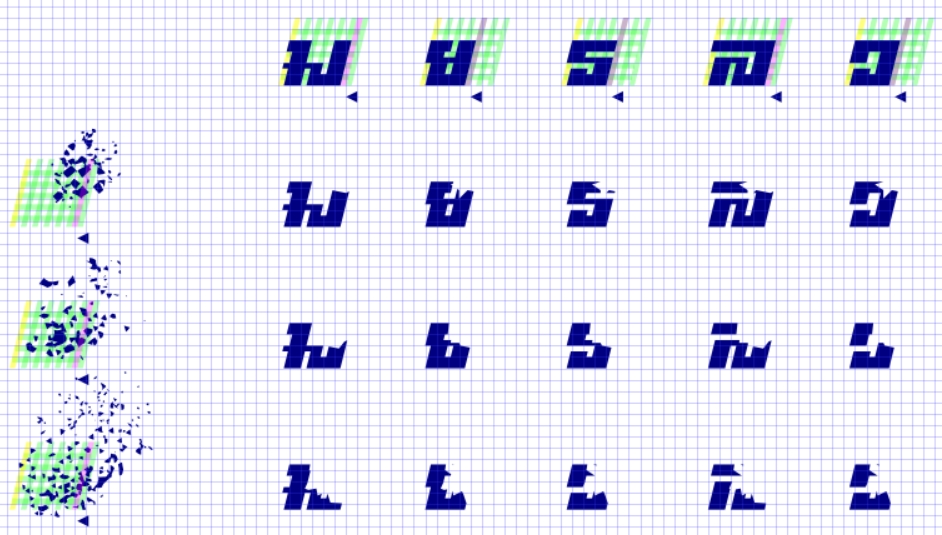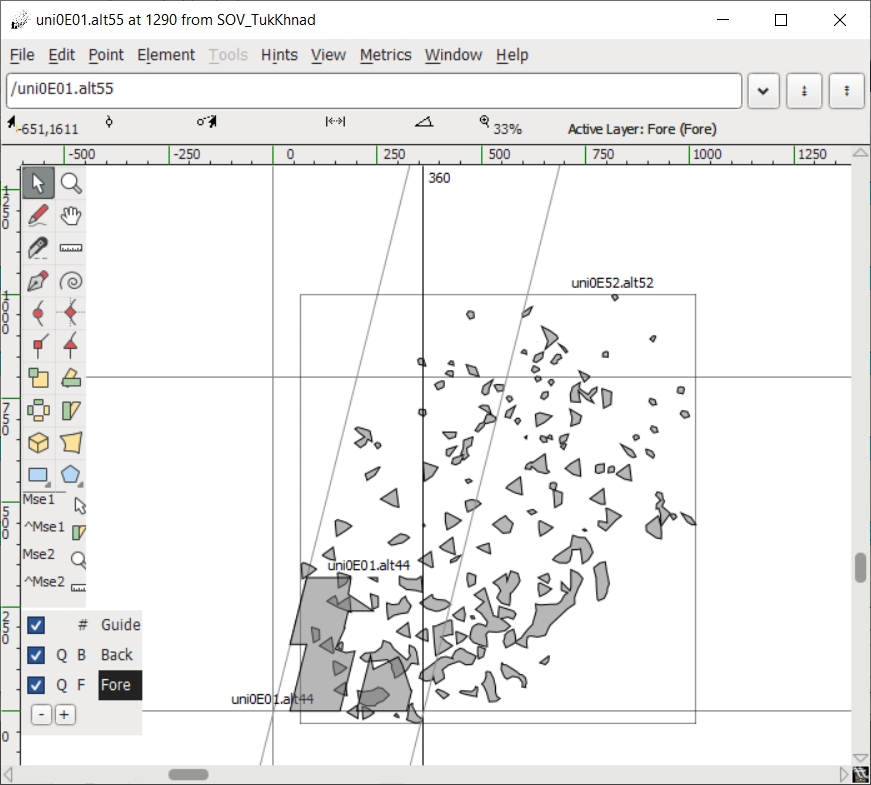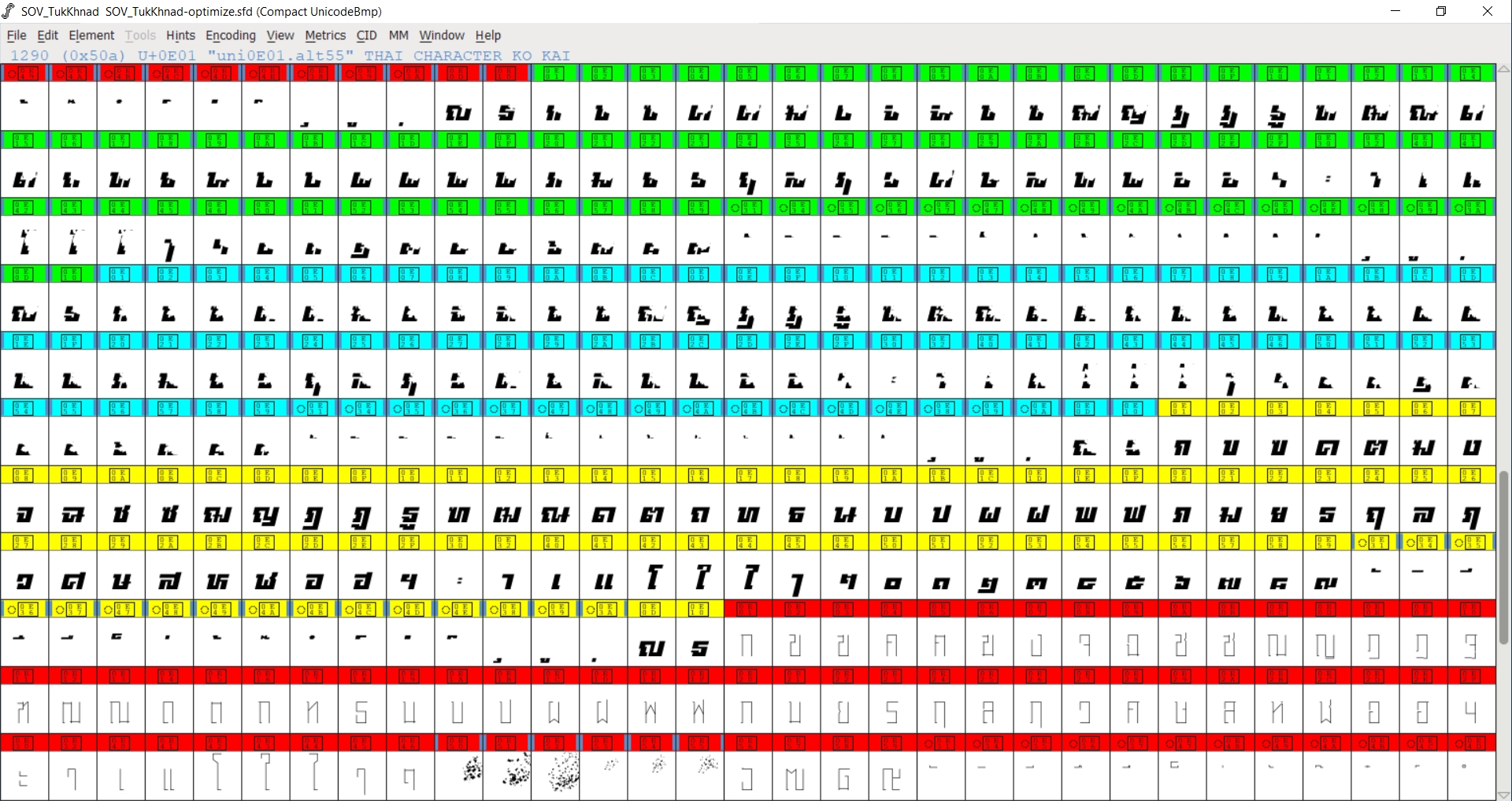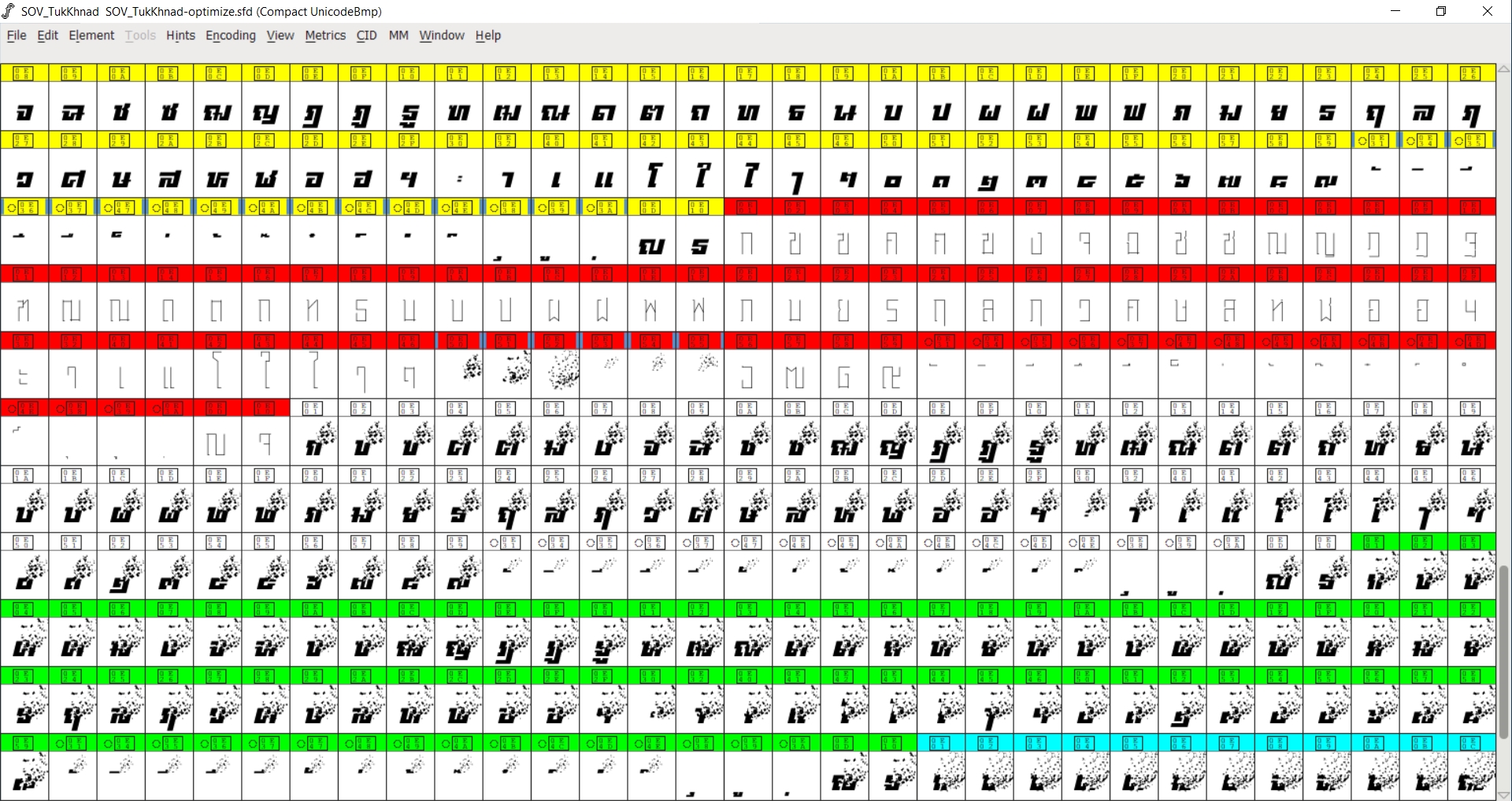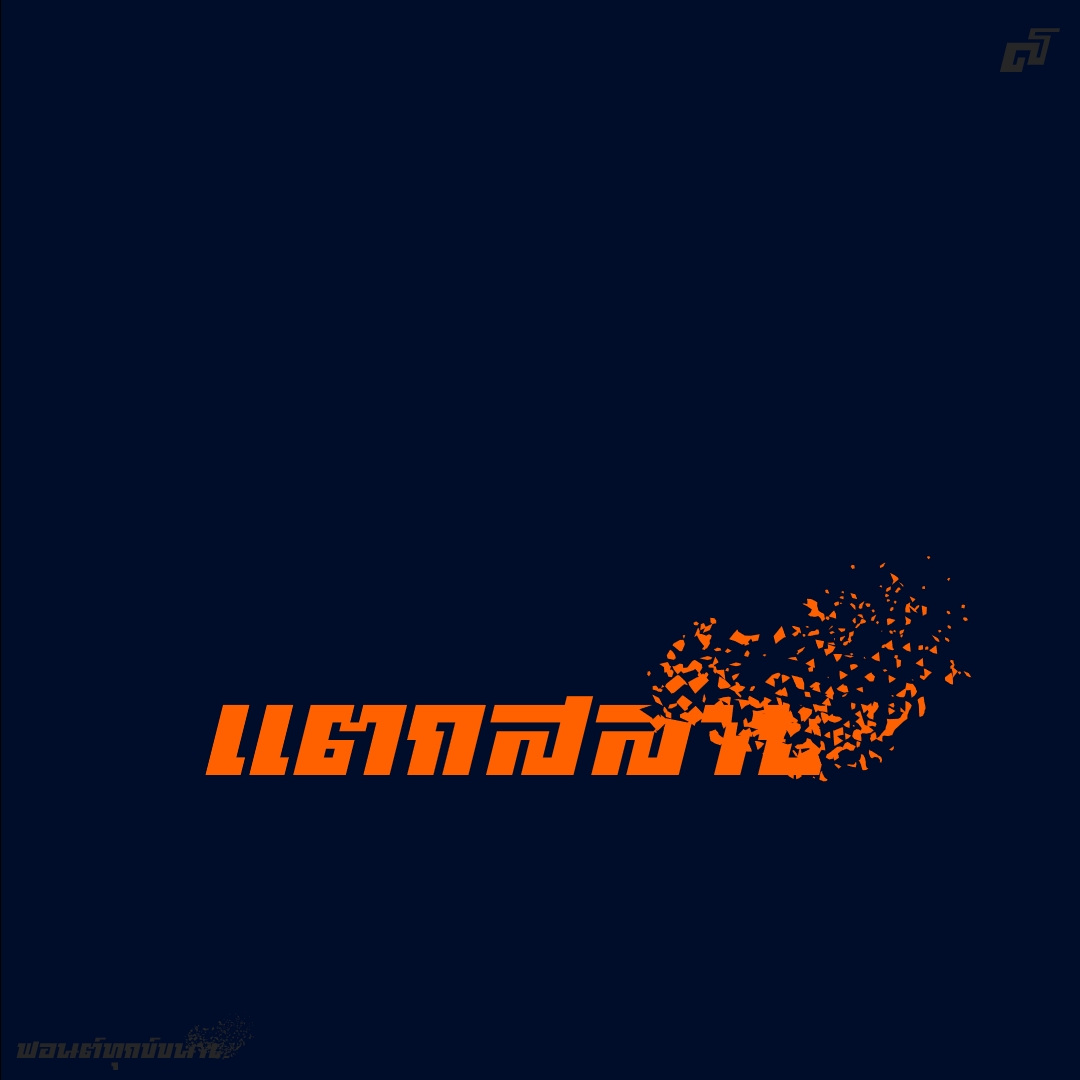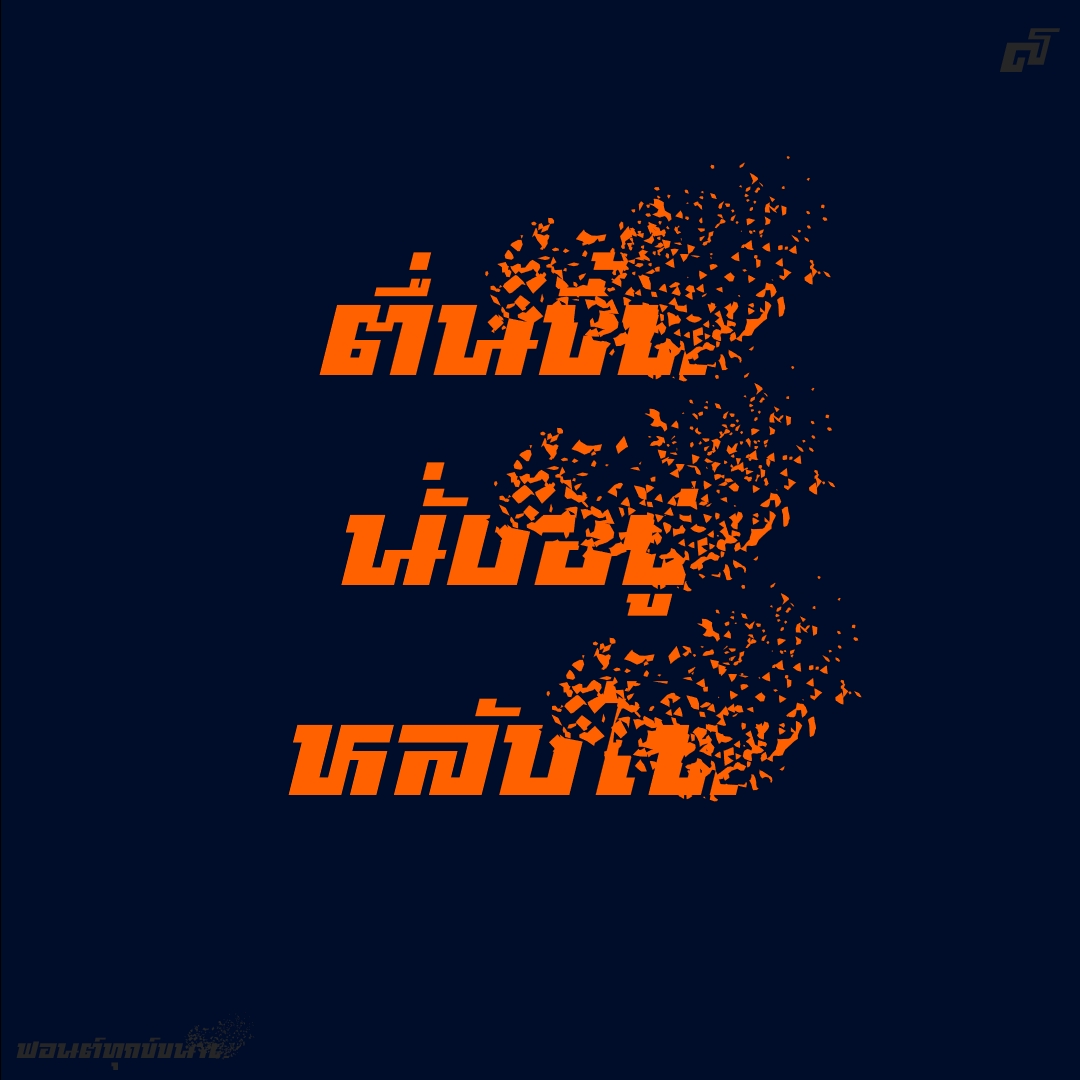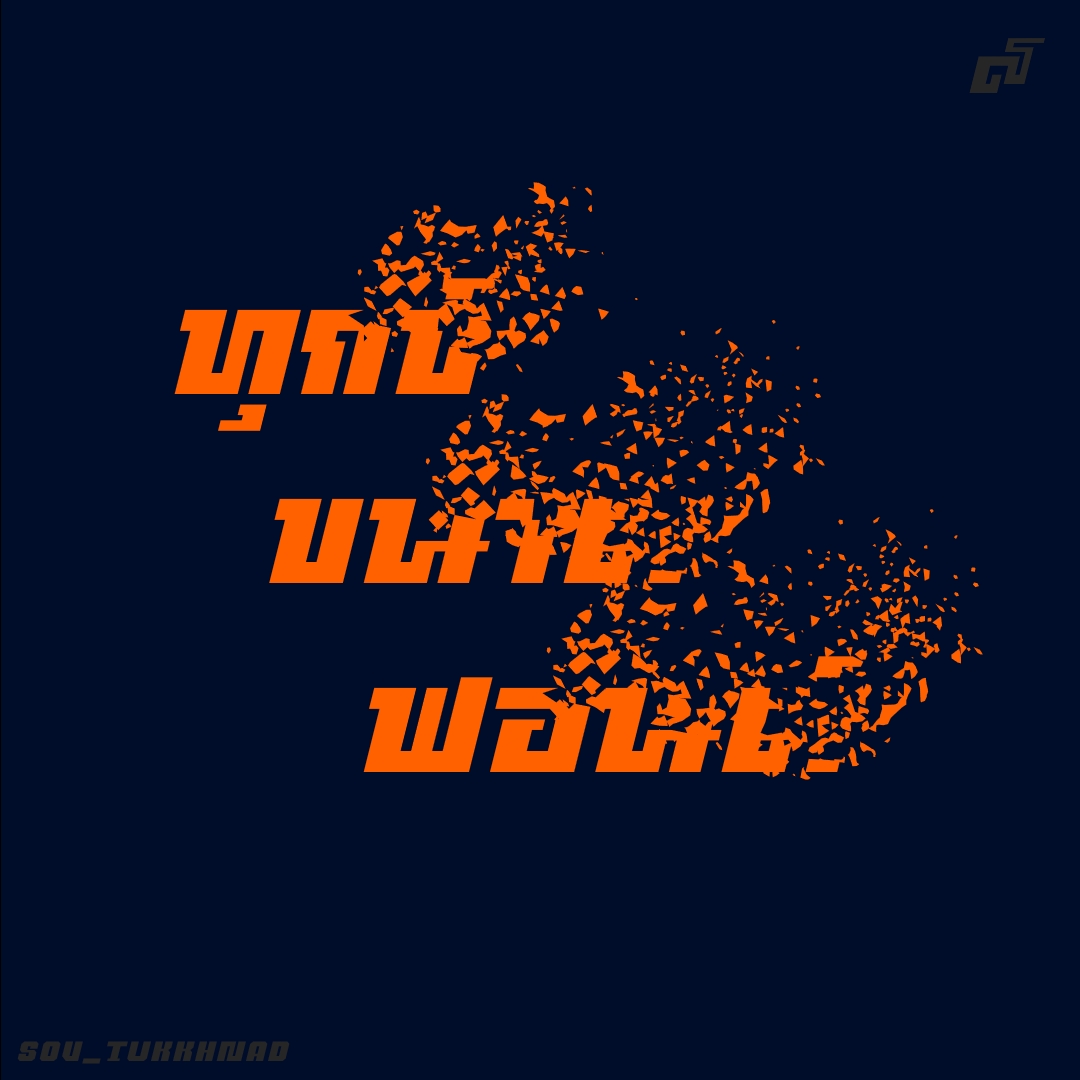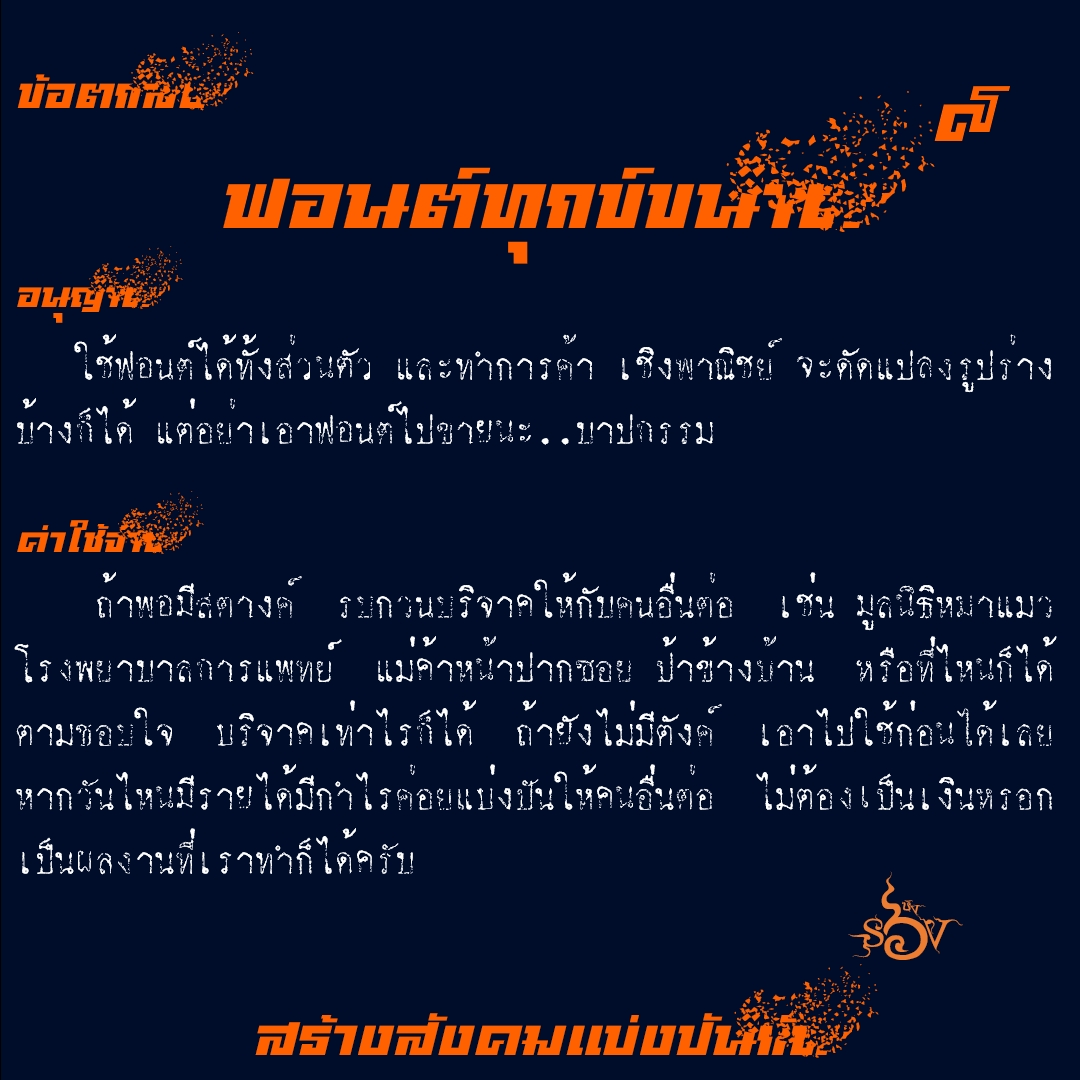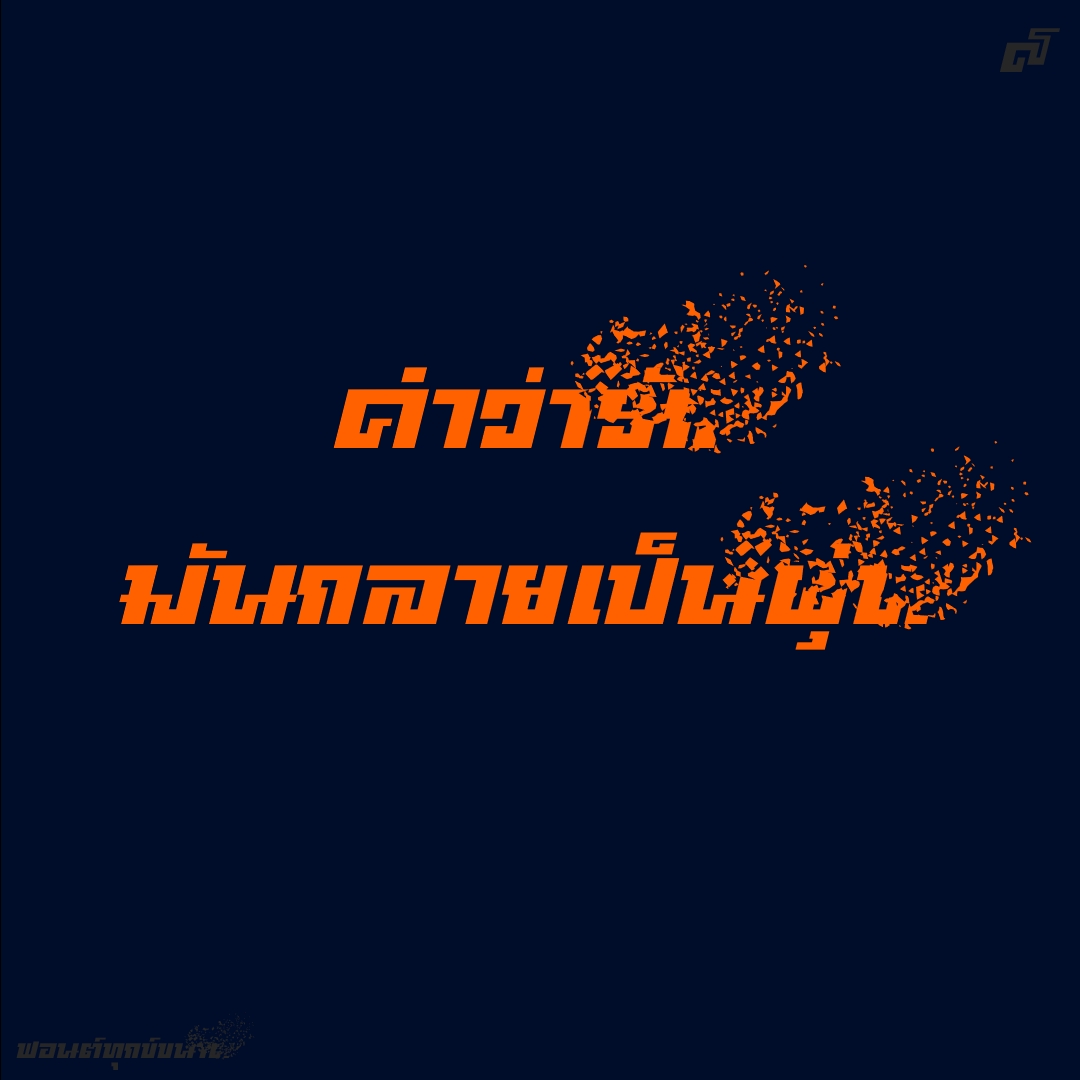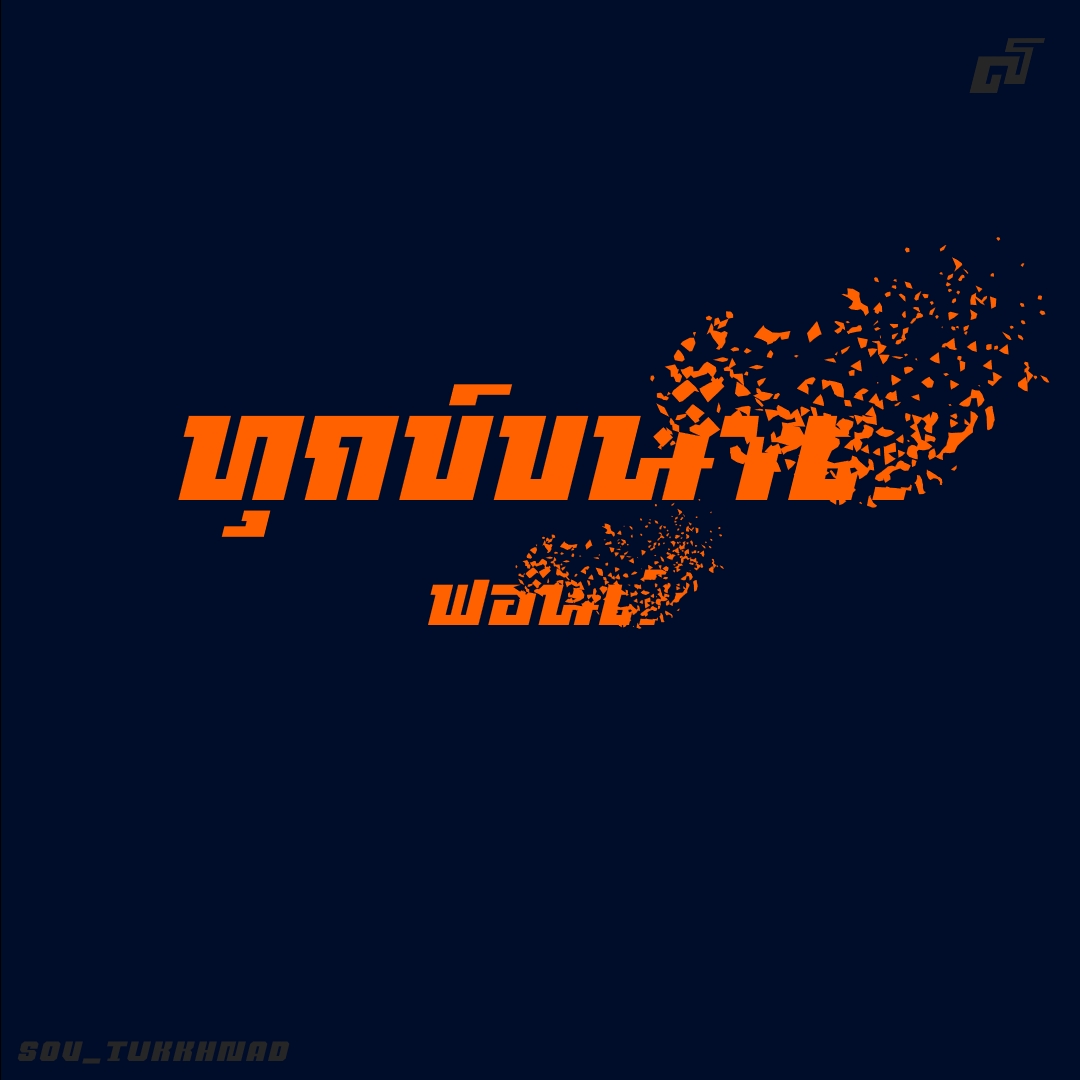
ฟอนต์ ทุกข์ขนาด
ฟอนต์ทุกข์ขนาด จาก คงขนาด หลายขนาด ไปต่อที่ ทุกขนาด (VF สินะ) พ้องเสียงเป็น ทุกข์ขนาด ทุกข์มาก ใจสลาย ก็เลยกลายเป็นฟอนต์นี้ ..ใช้เฉพาะทาง เหมาะแค่บางคำ บางประโยค นะ!
ชื่อฟอนต์ : ทุกข์ขนาด
ฟอนต์ทุกข์ขนาด จาก คงขนาด หลายขนาด ไปต่อที่ ทุกขนาด (VF สินะ) พ้องเสียงเป็น ทุกข์ขนาด ทุกข์มาก ใจสลาย ก็เลยกลายเป็นฟอนต์นี้ ..ใช้เฉพาะทาง เหมาะแค่บางคำ บางประโยค นะ!
ปรกติ ทำฟอนต์ยุบยิบแบบนี้จะขนาดใหญ่โตมาก.. เลยหาเทคนิคการลดขนาดฟอนต์ไว้ดังนี้
1. ออกแบบ แยกอักษร กัดกร่อน กับ เศษฝุ่น ออกจากกัน  เพื่อจะได้ใช้ ฝุ่นซ้ำๆได้ โดย link เอา
2. ตอนแรกทำแล้ว ก็ยังมีขนาด 400 กว่า K
3. เนื่องจาก เอาอักษร กัดกร่อน ตัวเต็มไปผสมกับ ตัวฝุ่นที่เป็น link -->  ต้องใช้ link ทั้งคู่ ตอน gen font ถึงจะไม่แปลง link เป็น vector จริงๆ
4. ก็เลยต้องทำชุดอักษร กัดกร่อน แยกออกไปอีก (แต่โชคดี template ฟอนต์นี้ มี 15 ชุดอักษร รอดตัวไป)
จบที่ เหลืออยู่ประมาณ 100 K